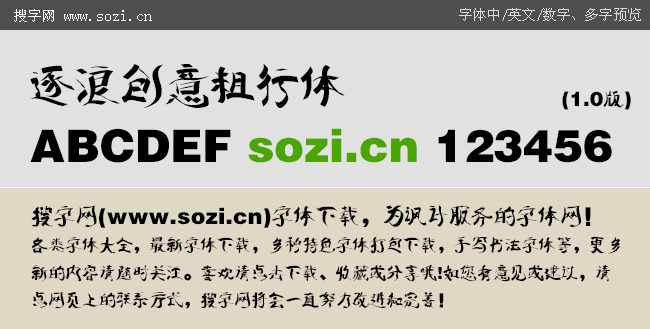
逐浪創意粗行體
搜字網提供一款逐浪創意粗行體中文書法字體下載,逐浪創意粗行體是一款手寫風格的書法創意字體,該字體瀟灑大方、筆勢強勁奔放,整體效果十分出色。適合應用于廣告設計、名片設計、包裝印刷、產品設計等應用。本字體僅供個人學習使用,如需商用請聯系作者進行購買(作者主頁http://www.ziti163.com/index.shtml)。